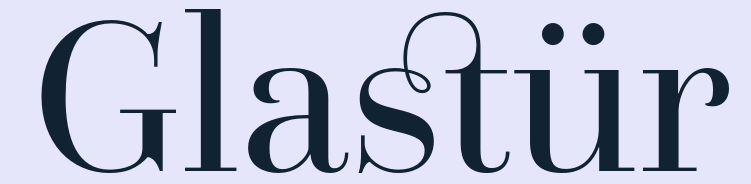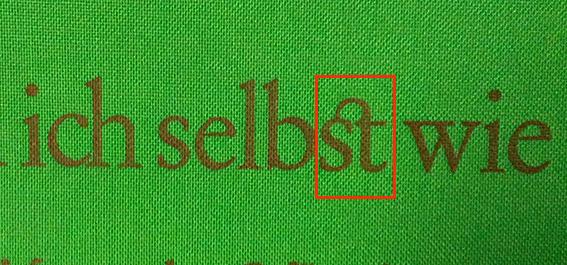
in meiner Handsatzwerkstatt befindet sich eine Garamond 48 Punkt. Diese hat viele Ligaturen aufzuweisen, deren Anwendung mir bekannt sind. Aber bei der Ligatur im beigelegten Foto bin ich mir nicht sicher. Wer weiß ob für diese Ligatur die gleichen Regeln gelten wie bspw. für ff, fl oder fi ?
Vielen Dank für die schnelle Antwort. Dann wäre also die Anwendung wie im beigefügten Bild so ok!
Aber …
Questa Grande
… sieht doch so schick aus! :mrgreen:
(Und dass es jemand nur wegen des kleinen Schnörkels falsch lesen würde, glaube ich auch eher weniger. Ich glaube, die einzigen, die – in Schauanwendungen – ein Problem mit der Ligatur dort hätten, wären Bedenkenträger, die die entsprechende Konvention kennen.)
Wer hinter der Gla-
stür sitzt, sollte nicht
mit Ligaturen werfen!
Ja, sieht trotzdem nicht unschnieke aus ...
(Und dass es jemand nur wegen des kleinen Schnörkels falsch lesen würde, glaube ich auch eher weniger.
Falsch lesen tue ich das nicht. Aber stören beim Lesen tut’s mich schon (und eigentlich immer noch, obwohl ich seit über einem halben Jahrhundert daran gewöhnt sein sollte).